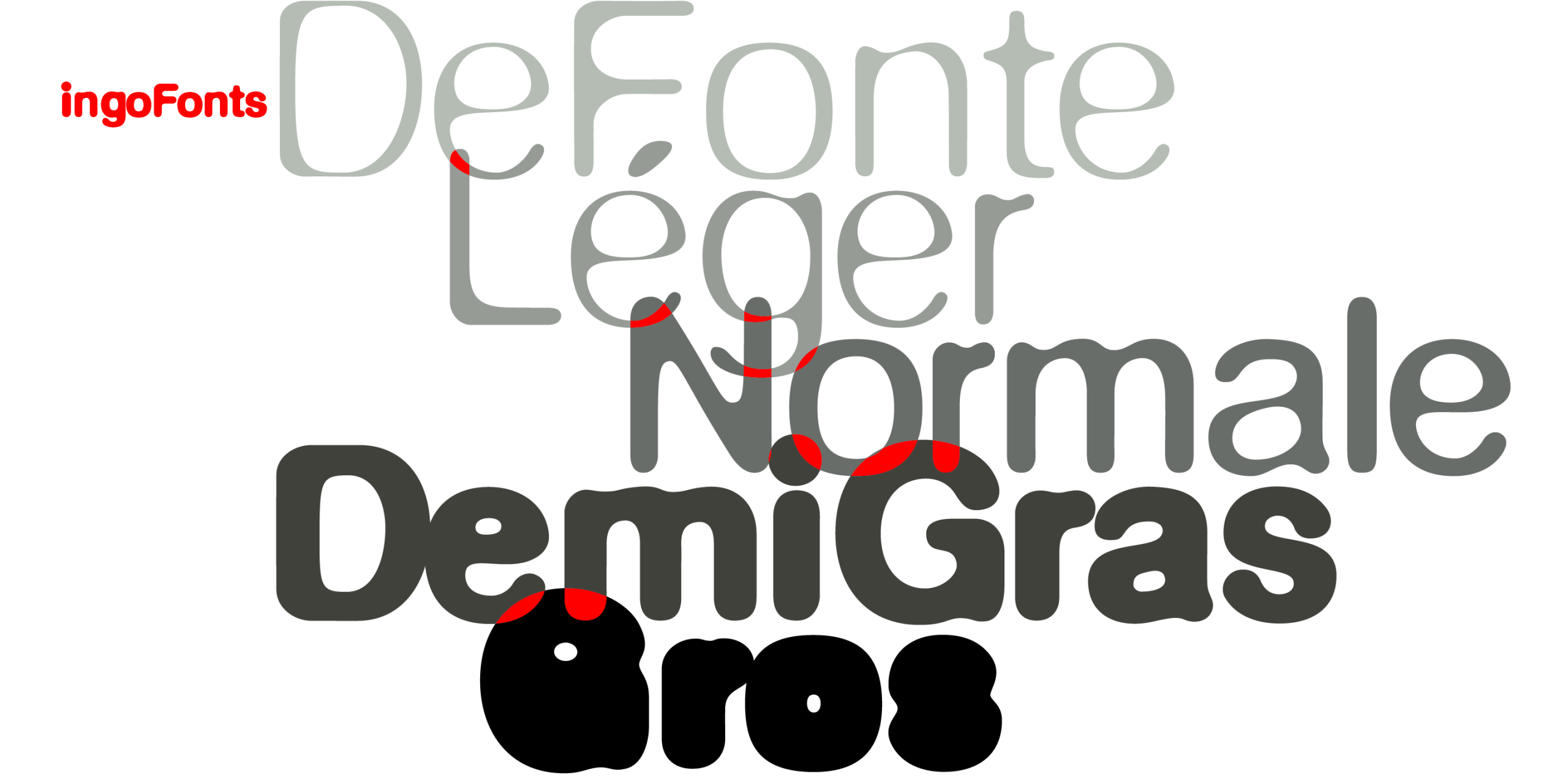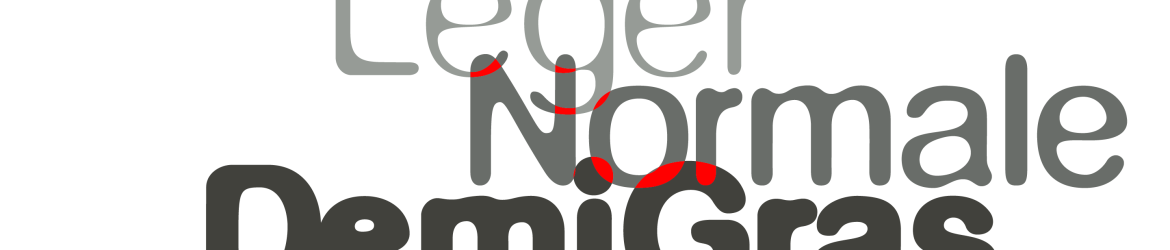
Descubra uma nova opção para seu próximo projeto de design: DeFonte Font Family. Esse novo conjunto de fuentes é um verdadeiro luxo para qualquer designer interessado em adicionar um toque de modernidade e elegância a suas criações. Desenvolvido pelo designer Hamilton, este famoso família DeFonte está disponível gratuitamente e sua influência está baseada no clássico “Helvetica”, que tanto fascina por ser simples e universal. A característica mais interessante dessa família DeFonte é o uso de um princípio distorcido para simular o efeito fotográfico da halosação ou sobreexposição. Este conceito criativo transforma a fonte, dando-lhe uma aparência vibrante e única. Seja você criando um logotipo impactante, estilizando uma capa de livro ou simplesmente adicionando um toque moderno à sua arte digital, DeFonte fornecerá os recursos para que seus trabalhos se destaquem. Estamos ansiosos para ver como você usará essa família DeFonte em seu próximo projeto!